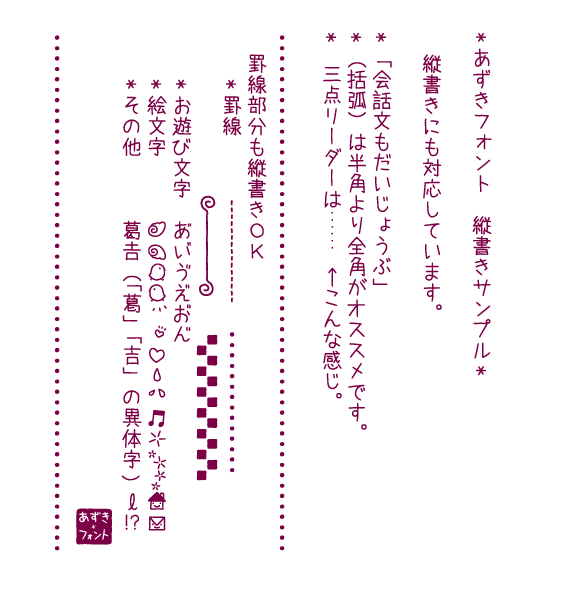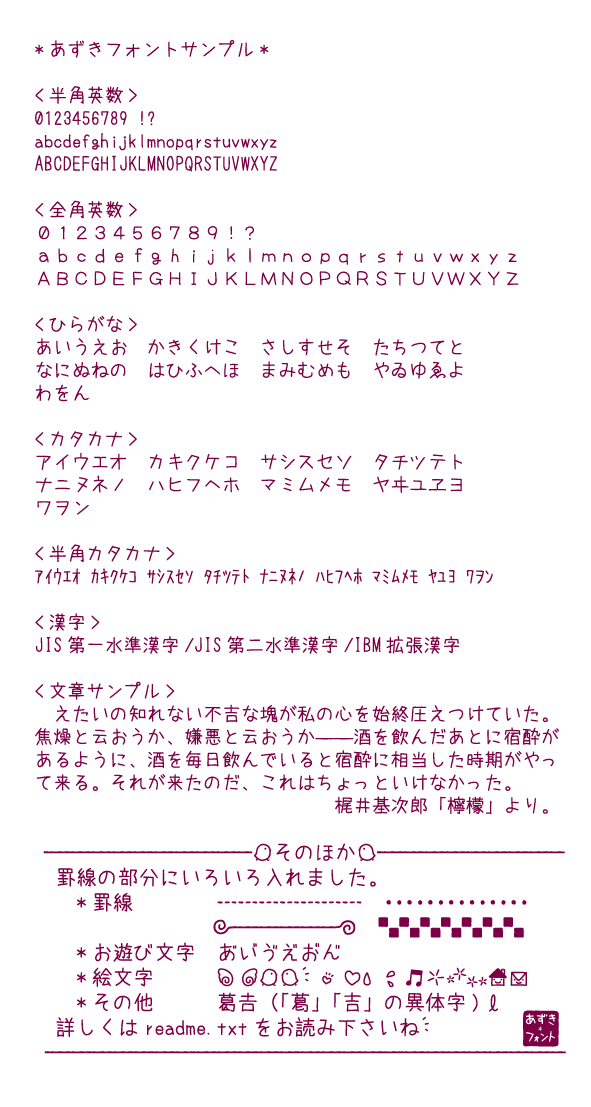
紅月字體字体信息
紅月字體
字体名称: 紅月字體
字体风格: 手写体
字体版权: 日向梓
原始手写字体。
“既不太严肃也不太可爱的字体”
它变成了一个清醒的结束。
推荐抗锯齿。
它可能不适合徽标,因为它很薄。
支持的字符
• 平假名和片假名
• 字母数字
• 汉字(JIS 级别 1、级别 2、IBM 扩展字符)
• 标点符号